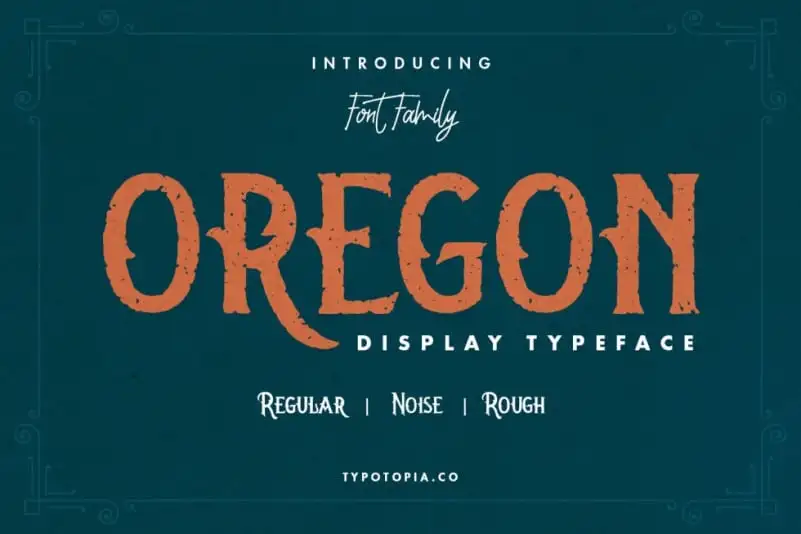
Oregon Display Font – Download Grátis
A fonte “Oregon Display Font” é uma escolha perfeita para quem busca transparência e modernidade em suas criações visuais. Com um estilo semi-vintage, essa tipografia atinge a complexidade com simplicidade, criando texturas que permitem uma estética única e distintiva. Especialmente perfeita para aplicação em elementos gráficos como logotipos, panfletos, embalagens ou até mesmo roupas de marca, a “Oregon Display Font” convida designers, publicitários e criativos a explorarem suas infinitas possibilidades. Com sua versatilidade, essa fonte não só trará um toque único às obras para o público final, mas também será uma ferramenta valiosa em qualquer projeto que exigir possua uma resolução clara e um design elegante.